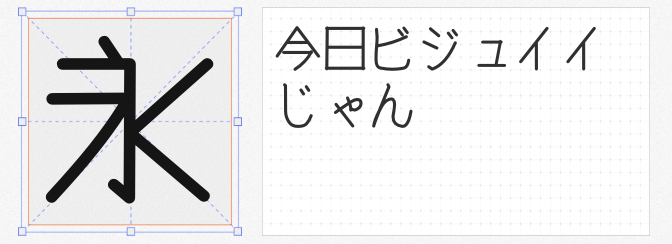
在平面设计中,字体的选择直接影响作品的视觉感染力。若你正在寻找既具可爱风格又能免费商用的日文字体,以下四款精选推荐将为你带来灵感与便利。它们风格各异却同样充满活力,无论是海报、品牌设计还是社交媒体素材,都能轻松驾驭。
香蕉Plus是一款融合“坚强骨骼”与“微可爱”气质的日文字体。其笔画粗细对比鲜明,横画纤细而竖画饱满,赋予文字挺拔的骨架,同时圆润的转折与柔和的弧度又为整体注入俏皮感。这种矛盾美学使它既能胜任需要存在感的标题设计,又能避免过于刻板。推荐用于儿童品牌、手账素材或需要活泼氛围的广告海报,轻松成为画面视觉中心。
原稿用标准书体以日本书法家稻泽淳二的丸风格手写体为蓝本,模拟真实书写痕迹,保留了纸张上的笔触质感与微妙墨迹变化。其字形略带不规则的倾斜感,仿佛一笔一划亲手书写,传递出温暖的手工感。适用于需要营造亲切氛围的设计,如咖啡馆菜单、手写体LOGO或包装插画,让冰冷的设计瞬间充满人文温度。
作为经典马克笔手绘体的升级版,Yusei魔法手写体通过“极粗纵画”与“纤细横画”的对比,创造出独特的视觉韵律。粗笔触模拟马克笔的力度感,细横线则像笔尖轻扫而过,既保留手写字的随性,又提升文字在复杂背景中的可读性。推荐用于活动海报标题、漫画字幕或需要强调速度感的动态设计,粗细交错的笔画如同魔法般抓住观众视线。
由Fontworks开源的摇滚乐 One,以原始流行风格为基调,通过力度多变的笔触与圆形点缀营造跃动感。粗笔画末端微微散开的笔触如同音乐节奏的延伸,而点缀在字母间的圆点则像跳动的音符,为字体注入无限活力。适用于音乐节海报、潮流品牌或儿童相关设计,即使是全大写排版也能保持轻松不压抑,是传递快乐能量的绝佳选择。